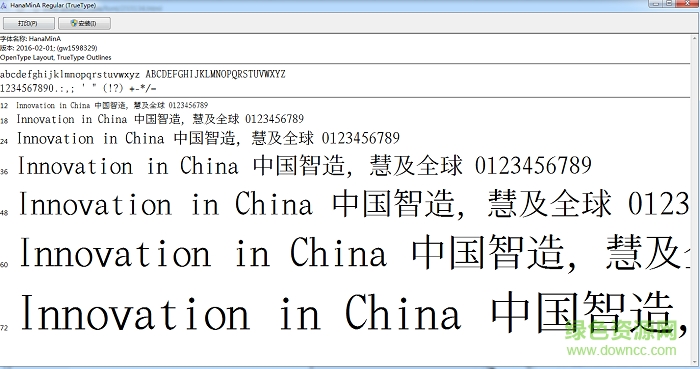
花園明朝a字體是一款類似于宋體的日文字體,保留了一般宋體的特點(diǎn),這款字體清秀、古樸,字型秀美,可以用于書籍目錄、正文排版、宣傳用字等方面,需要的朋友快來下載吧!
元明時(shí)期,戲曲小說的大量刊行,對(duì)雕版印刷技術(shù)有了新的要求。為了提高效率,雕版師傅們不約而同地開始對(duì)字體進(jìn)行改良,最終形成了一種橫細(xì)豎粗的,專為印刷雕版使用的字體,也就是宋體字。宋體字在明朝時(shí)傳入日本,因而日本稱之為“明體”或“明朝體”。